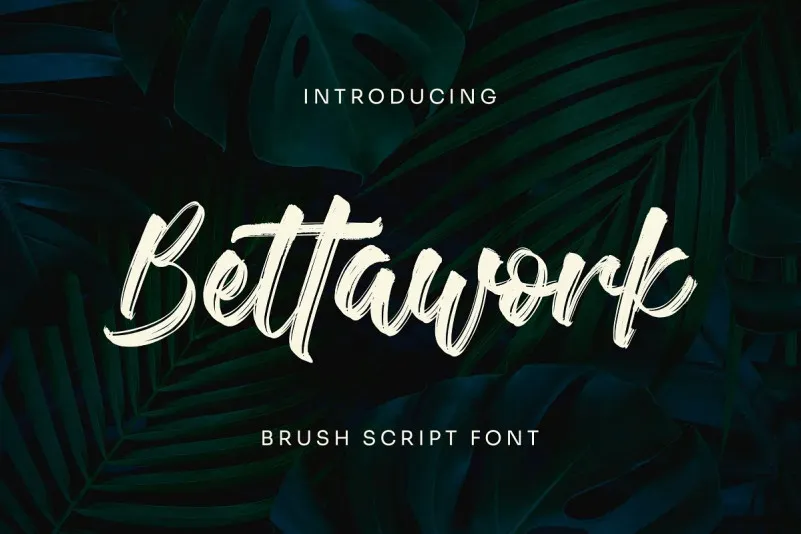
Bettawork Font – Download Grátis
A Bettawork Font é uma elegante escolha para aqueles que buscam algo diferente na categoria de fontes script. Desenvolvida com cuidado pela 99designs, essa fonte possui um toque descontraído e divertido, inspirada nos desenhos feitos a mão em papéis e depois transformados em formatos vetorizados. Suas letras ganham vida ao serem criadas diretamente com ferramentas de pintura, garantindo uma aparência mais natural aos seus projetos. Se você deseja um texto que se destaca por sua autenticidade e naturalidade, a Bettawork é perfeita para isso. Os designers também podem explorar as alternativas e ligaturas presentes na fonte para criar textos ainda mais interessantes e personalizados. Esta font é particularmente adequada para projetos de embalagens de produtos, identidades empresariais, design de logomarcas ou criação de um slogan único. Seu estilo descontraído e elegante torna-a uma opção perfeita tanto para designers quanto para pessoas que simplesmente desejam dar um toque diferente a seus materiais digitais. Experimente Bettawork Font em seu próximo projeto gráfico e descubra por si mesmo o encanto de sua aparência natural e divertida.